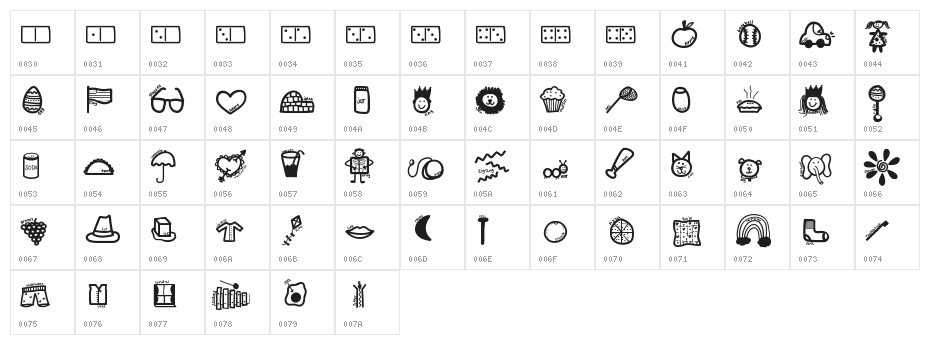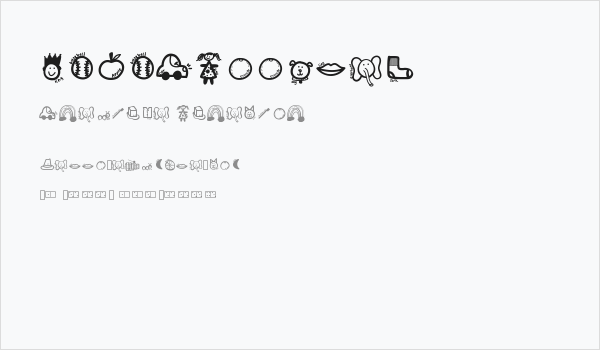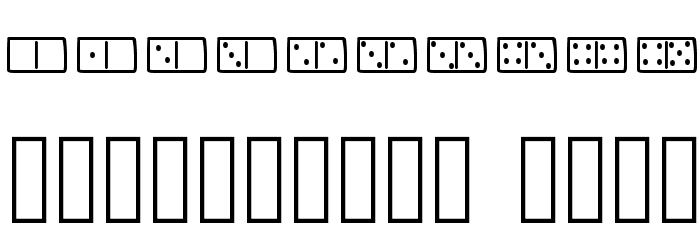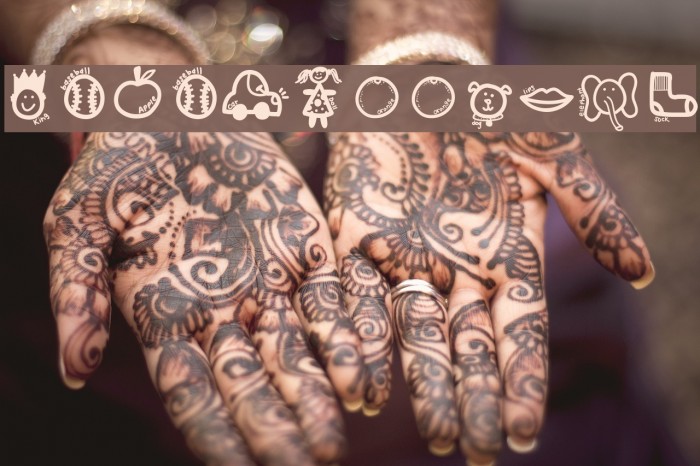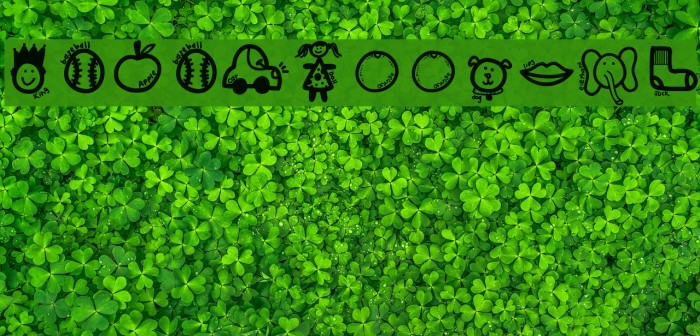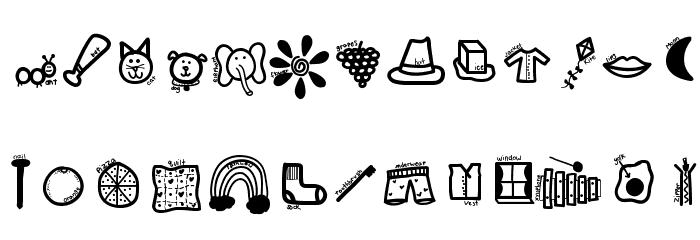
KBABCDoodles Font
Fonts by Khrys Bosland
| Gesamtstil | Playful, Whimsical |
| Anwendungsfall | Illustrations, Educational materials, Creative projects |
| Vorgeschlagene Projekte | Ideal for children's books, educational materials, playful branding, and creative crafts. |